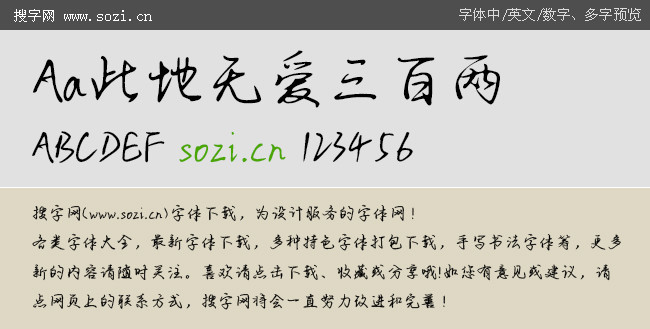
Aa此地?zé)o愛三百兩字體
搜字網(wǎng)給大家提供一款A(yù)a此地?zé)o愛三百兩字體中文書法字體下載,這是一款非常漂亮的硬筆書法字體,書寫流暢,瀟灑大方,適合海報(bào)設(shè)計(jì)、畫冊(cè)設(shè)計(jì),廣告設(shè)計(jì)等應(yīng)用(此字體為個(gè)人非商用版,如需商用請(qǐng)聯(lián)系作者購買版權(quán))。